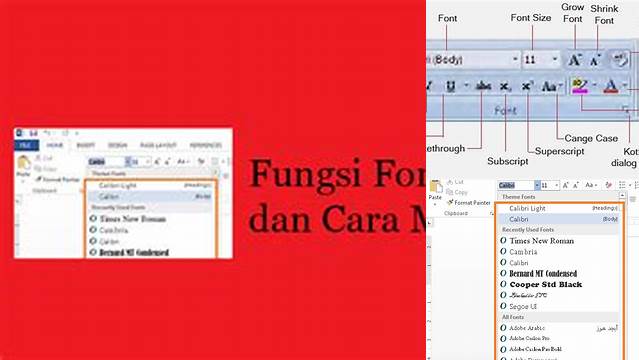
Fungsi Font Di Word: Panduan Lengkap & Tips Memilih
Pendahuluan
Guys, pernah gak sih kalian bertanya-tanya, sebenarnya apa aja sih fungsi font di Microsoft Word? Nah, di artikel ini, kita bakal bahas tuntas semua tentang fungsi font pada Microsoft Word. Mulai dari dasar-dasar pemilihan font, pengaturan ukuran, gaya, efek, hingga tips dan trik untuk membuat dokumen kamu jadi lebih menarik dan profesional. Jadi, simak terus ya!
Dalam dunia pengolahan kata, fungsi font memegang peranan yang sangat krusial. Font bukan hanya sekadar tentang bagaimana teks terlihat, tapi juga tentang bagaimana pesan yang ingin kamu sampaikan tersampaikan dengan efektif. Pemilihan font yang tepat dapat meningkatkan keterbacaan, menarik perhatian pembaca, dan memberikan kesan profesional pada dokumen kamu. Bayangkan jika kamu membaca sebuah laporan penting dengan font yang sulit dibaca atau terlalu ramai, pasti akan sangat mengganggu, kan? Oleh karena itu, pemahaman yang baik tentang fungsi font pada Microsoft Word sangat penting untuk siapa saja yang sering menggunakan aplikasi ini, baik untuk keperluan pribadi, akademis, maupun profesional. Dengan menguasai fungsi font, kamu bisa membuat dokumen yang tidak hanya informatif, tetapi juga enak dilihat dan dibaca.
Microsoft Word menyediakan berbagai macam fungsi font yang bisa kamu manfaatkan. Mulai dari pemilihan jenis font yang beragam, pengaturan ukuran, gaya (seperti bold, italic, dan underline), hingga efek-efek khusus yang bisa membuat teks kamu semakin menarik. Selain itu, kamu juga bisa mengatur warna font, spasi antar karakter, dan masih banyak lagi. Dengan semua fungsi font ini, kamu memiliki kendali penuh atas tampilan teks pada dokumen kamu. Namun, dengan banyaknya pilihan yang tersedia, terkadang kita merasa bingung font mana yang sebaiknya digunakan untuk keperluan tertentu. Misalnya, font apa yang cocok untuk membuat surat lamaran kerja, font apa yang ideal untuk laporan akademis, atau font apa yang pas untuk presentasi bisnis. Di sinilah pentingnya kita memahami fungsi font secara mendalam. Dalam artikel ini, kita akan membahas berbagai aspek fungsi font pada Microsoft Word, mulai dari dasar hingga tips dan trik yang lebih lanjut. Jadi, pastikan kamu mengikuti artikel ini sampai selesai ya, guys!
Apa Itu Font dan Mengapa Penting?
Sebelum kita membahas lebih jauh tentang fungsi font pada Microsoft Word, ada baiknya kita pahami dulu apa itu font dan mengapa font itu penting. Secara sederhana, font adalah desain visual dari huruf, angka, simbol, dan karakter lainnya. Setiap font memiliki karakteristik unik yang membedakannya dari font lainnya. Ada font yang terlihat formal, ada yang kasual, ada yang modern, dan ada pula yang klasik. Pemilihan font yang tepat dapat memberikan nuansa tertentu pada dokumen kamu dan memengaruhi bagaimana pesan kamu diterima oleh pembaca. Fungsi font sangat penting dalam komunikasi visual. Misalnya, penggunaan font yang tebal dan besar dapat menarik perhatian pada judul atau headline, sedangkan font yang lebih sederhana dan mudah dibaca cocok untuk teks isi.
Pentingnya fungsi font dalam sebuah dokumen tidak bisa diremehkan. Font bukan hanya tentang estetika, tapi juga tentang keterbacaan dan efektivitas komunikasi. Font yang mudah dibaca akan membuat pembaca lebih nyaman dan fokus pada isi teks. Sebaliknya, font yang sulit dibaca atau terlalu ramai bisa membuat pembaca cepat lelah dan kehilangan minat. Selain itu, font juga dapat mencerminkan kepribadian atau gaya dari dokumen yang kamu buat. Misalnya, dokumen formal seperti laporan bisnis atau surat lamaran kerja sebaiknya menggunakan font yang profesional dan mudah dibaca, seperti Times New Roman atau Arial. Sementara itu, untuk dokumen yang lebih kasual atau kreatif, kamu bisa menggunakan font yang lebih unik dan ekspresif, seperti Comic Sans MS atau Brush Script MT (meskipun penggunaan font ini perlu hati-hati, ya!). Intinya, fungsi font adalah untuk menyampaikan pesan dengan jelas dan efektif, sekaligus memberikan kesan yang sesuai dengan tujuan dokumen.
Dalam konteks Microsoft Word, fungsi font menjadi semakin penting karena aplikasi ini menyediakan berbagai macam pilihan font yang bisa kamu gunakan. Mulai dari font bawaan yang sudah terinstal di komputer kamu, hingga font-font tambahan yang bisa kamu unduh dan instal sendiri. Dengan banyaknya pilihan ini, kamu memiliki fleksibilitas untuk memilih font yang paling sesuai dengan kebutuhan dan preferensi kamu. Namun, banyaknya pilihan ini juga bisa menjadi tantangan tersendiri. Bagaimana cara memilih font yang tepat dari sekian banyak pilihan yang ada? Bagaimana cara memadukan font yang berbeda agar terlihat harmonis? Nah, pertanyaan-pertanyaan ini akan kita bahas lebih lanjut di bagian-bagian berikutnya dari artikel ini. Jadi, tetaplah bersama kami ya!
Fungsi Utama Font di Microsoft Word
Sekarang, mari kita bahas fungsi utama font di Microsoft Word. Secara umum, fungsi font dapat dikelompokkan menjadi beberapa kategori, yaitu:
1. Memilih Jenis Font
Fungsi font yang paling mendasar adalah memilih jenis font yang akan digunakan. Microsoft Word menyediakan ratusan jenis font yang berbeda, mulai dari yang klasik hingga yang modern, dari yang formal hingga yang kasual. Setiap jenis font memiliki karakteristik unik yang memengaruhi tampilan dan kesan teks. Misalnya, font serif (seperti Times New Roman) memiliki kait kecil di ujung huruf yang membuatnya terlihat lebih formal dan mudah dibaca dalam teks panjang. Sementara itu, font sans-serif (seperti Arial) tidak memiliki kait dan terlihat lebih bersih dan modern, sehingga cocok untuk judul atau headline. Pemilihan jenis font yang tepat sangat penting untuk memastikan dokumen kamu mudah dibaca dan sesuai dengan tujuan kamu.
2. Mengatur Ukuran Font
Selain jenis font, fungsi font juga mencakup pengaturan ukuran font. Ukuran font diukur dalam point (pt). Semakin besar angka point, semakin besar ukuran font. Ukuran font yang tepat sangat penting untuk keterbacaan dokumen. Ukuran font yang terlalu kecil bisa membuat pembaca kesulitan membaca teks, sedangkan ukuran font yang terlalu besar bisa terlihat tidak profesional dan memakan terlalu banyak ruang. Umumnya, ukuran font 12 pt dianggap ideal untuk teks isi dalam dokumen formal. Namun, ukuran font bisa disesuaikan tergantung pada jenis dokumen, target pembaca, dan preferensi pribadi. Judul biasanya menggunakan ukuran font yang lebih besar daripada teks isi untuk menarik perhatian dan memberikan struktur pada dokumen.
3. Mengatur Gaya Font
Gaya font adalah fungsi font yang memungkinkan kamu untuk mengubah tampilan teks menjadi bold (tebal), italic (miring), underline (garis bawah), atau kombinasi dari ketiganya. Gaya font ini digunakan untuk memberikan penekanan pada kata atau frasa tertentu, membuat judul atau subjudul lebih menonjol, atau menandai kutipan atau istilah asing. Penggunaan gaya font yang tepat dapat membantu pembaca memindai dokumen dengan cepat dan memahami poin-poin penting. Namun, penggunaan gaya font yang berlebihan bisa membuat dokumen terlihat berantakan dan sulit dibaca. Jadi, gunakan gaya font dengan bijak dan sesuai kebutuhan.
4. Mengatur Warna Font
Warna font adalah fungsi font yang memungkinkan kamu untuk mengubah warna teks. Microsoft Word menyediakan berbagai macam pilihan warna, mulai dari warna-warna dasar hingga warna-warna yang lebih kompleks. Warna font bisa digunakan untuk memberikan penekanan pada teks, membedakan bagian-bagian dokumen, atau sekadar membuat dokumen terlihat lebih menarik. Namun, pemilihan warna font juga perlu diperhatikan. Warna font yang terlalu terang atau terlalu gelap bisa sulit dibaca, terutama jika latar belakang dokumen juga memiliki warna yang senada. Sebaiknya, gunakan warna font yang kontras dengan latar belakang agar teks mudah dibaca. Selain itu, hindari penggunaan terlalu banyak warna dalam satu dokumen, karena bisa membuat dokumen terlihat ramai dan tidak profesional.
5. Menambahkan Efek Font
Microsoft Word juga menyediakan berbagai efek font yang bisa kamu gunakan untuk membuat teks kamu semakin menarik. Beberapa efek font yang umum digunakan antara lain shadow (bayangan), outline (garis luar), glow (cahaya), dan reflection (pantulan). Efek font bisa digunakan untuk memberikan dimensi pada teks, membuat teks lebih menonjol, atau sekadar menambahkan sentuhan kreatif pada dokumen. Namun, sama seperti gaya font dan warna font, penggunaan efek font juga perlu diperhatikan. Efek font yang berlebihan bisa membuat teks sulit dibaca dan mengganggu tampilan keseluruhan dokumen. Jadi, gunakan efek font dengan bijak dan sesuai kebutuhan.
Tips Memilih Font yang Tepat
Memilih font yang tepat adalah kunci untuk membuat dokumen yang efektif dan profesional. Berikut ini beberapa tips yang bisa kamu ikuti:
Pertimbangkan Tujuan Dokumen: Fungsi font harus selaras dengan tujuan dokumen. Apakah kamu membuat laporan formal, presentasi bisnis, surat lamaran kerja, atau undangan pesta? Setiap jenis dokumen membutuhkan jenis font yang berbeda. Untuk dokumen formal, gunakan font yang profesional dan mudah dibaca seperti Times New Roman atau Arial. Untuk dokumen yang lebih kasual, kamu bisa menggunakan font yang lebih kreatif, tapi tetap pastikan mudah dibaca.
Perhatikan Target Pembaca: Siapa yang akan membaca dokumen kamu? Apakah mereka kolega bisnis, dosen, teman, atau keluarga? Pilihlah font yang sesuai dengan selera dan preferensi target pembaca kamu. Misalnya, jika kamu membuat presentasi untuk audiens yang lebih muda, kamu bisa menggunakan font yang lebih modern dan catchy. Namun, jika kamu membuat laporan untuk atasan kamu, sebaiknya gunakan font yang lebih formal dan profesional.
Prioritaskan Keterbacaan: Fungsi font yang paling penting adalah keterbacaan. Pilihlah font yang mudah dibaca dalam berbagai ukuran dan gaya. Hindari font yang terlalu rumit atau memiliki dekorasi yang berlebihan, karena bisa membuat pembaca kesulitan membaca teks. Uji coba font yang berbeda dengan mencetak beberapa contoh teks dan lihat mana yang paling mudah dibaca.
Padukan Font dengan Bijak: Memadukan font yang berbeda bisa membuat dokumen kamu terlihat lebih menarik dan dinamis. Namun, jangan memadukan terlalu banyak font dalam satu dokumen. Sebaiknya, batasi penggunaan font maksimal tiga jenis. Padukan font yang memiliki kontras yang cukup, misalnya font serif untuk teks isi dan font sans-serif untuk judul. Hindari memadukan font yang terlalu mirip, karena bisa membuat dokumen terlihat monoton.
Perhatikan Lisensi Font: Beberapa font memiliki lisensi yang membatasi penggunaannya. Pastikan kamu memiliki hak untuk menggunakan font yang kamu pilih, terutama jika kamu membuat dokumen untuk tujuan komersial. Ada banyak situs web yang menyediakan font gratis untuk penggunaan pribadi maupun komersial. Namun, selalu periksa lisensi font sebelum menggunakannya.
Mengoptimalkan Penggunaan Font di Microsoft Word
Setelah memilih font yang tepat, kamu juga perlu tahu cara mengoptimalkan penggunaannya di Microsoft Word. Berikut ini beberapa tips dan trik yang bisa kamu coba:
Gunakan Gaya (Styles): Microsoft Word memiliki fungsi font Styles yang memungkinkan kamu untuk membuat format teks yang konsisten di seluruh dokumen. Dengan menggunakan Styles, kamu bisa dengan mudah mengubah jenis font, ukuran, gaya, dan warna untuk seluruh bagian dokumen hanya dengan beberapa klik. Ini sangat berguna untuk membuat dokumen yang panjang dan kompleks.
Manfaatkan Fitur Font Themes: Font Themes adalah fungsi font yang memungkinkan kamu untuk memilih kombinasi font yang sudah dirancang sebelumnya. Microsoft Word menyediakan beberapa Font Themes yang bisa kamu gunakan. Kamu juga bisa membuat Font Theme sendiri dengan memadukan font yang berbeda. Font Themes sangat berguna untuk membuat dokumen yang memiliki tampilan yang konsisten dan profesional.
Perhatikan Spasi Antar Karakter dan Baris: Selain jenis font, ukuran, dan gaya, spasi antar karakter dan baris juga memengaruhi keterbacaan dokumen. Atur spasi antar karakter dan baris agar teks tidak terlalu rapat atau terlalu renggang. Microsoft Word menyediakan fungsi font untuk mengatur spasi antar karakter (kerning) dan spasi antar baris (line spacing).
Gunakan Fitur Clear Formatting: Terkadang, ketika kita menyalin teks dari sumber lain, format font dari sumber tersebut ikut terbawa ke dokumen kita. Ini bisa membuat dokumen terlihat tidak konsisten dan berantakan. Microsoft Word memiliki fungsi font Clear Formatting yang memungkinkan kamu untuk menghapus semua format teks dan mengembalikannya ke format default. Fitur ini sangat berguna untuk membersihkan format teks yang tidak diinginkan.
Eksplorasi Font yang Berbeda: Jangan takut untuk bereksperimen dengan font yang berbeda. Cobalah font-font baru yang belum pernah kamu gunakan sebelumnya. Kamu mungkin akan menemukan font yang sangat cocok dengan gaya dan kepribadian kamu. Ada banyak situs web yang menyediakan font gratis yang bisa kamu unduh dan instal di komputer kamu.
Kesimpulan
Nah, itu dia pembahasan lengkap tentang fungsi font pada Microsoft Word. Semoga artikel ini bermanfaat untuk kamu ya, guys! Ingat, fungsi font bukan hanya tentang memilih font yang bagus, tapi juga tentang memahami bagaimana font dapat memengaruhi pesan yang ingin kamu sampaikan. Dengan memahami fungsi font secara mendalam, kamu bisa membuat dokumen yang tidak hanya informatif, tetapi juga enak dilihat dan dibaca. Jadi, jangan ragu untuk bereksperimen dan menemukan font yang paling sesuai dengan kebutuhan dan preferensi kamu. Selamat mencoba!